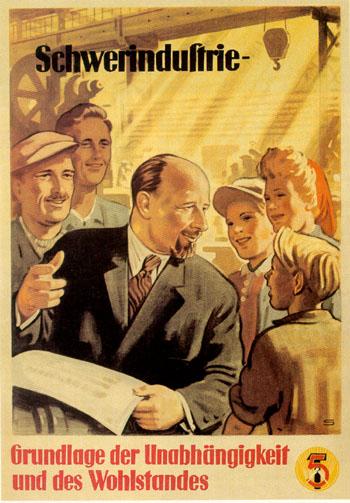
Schließen?! Wo, wenn nicht im Typoforum unter einem thread mit dem Titel Lang-? soll denn über dieses Problem gestritten werden?! Und es wird ja auch niemand gezwungen mitzulesen.
Es wäre vielleicht interessant die verschiedenen Argumente nochmal so zu präzisieren, dass man sich die nächste Debatte zu dem Thema sparen kann mit dem Verweis auf diesen thread. Da wäre den jetzt zu schließen aber wenig hilfreich, dann geht der ganze Spaß beim nächsten mal von vorn los.
Zum Thema:
Ich stimme Thierry zu - Kleinschreibung ist für den Durchschnittsleser weniger irritierend als die verwendung zweier s-Formen.
Ich stimme aber auch Pachulke zu - Die Intension desjenigen der das lange s verwendendet ist vermutlich in den meisten Fällen edler als die desjenigen, der alles klein schreibt. Die Kleinschreibung reduziert die Differenzierungsmöglichkeiten, wärend die verwendung des lange s diese erweitert.
Die Verwendung des langen s führt eine weitere mehr oder weniger komplizierte Regel ein, wärend die konsequente Kleinschreibung eine einfache Regel ignoriert. Das Problem, das es abzuwegen gilt, ist also - Einfachheit gegen Differenzierung. Ich denke, grundsätzlich sind beide erstrebenswert.
vielleicht können wir uns ja auf einen kompromi?s einigen: ? + klein?chreibung ...
Ich meinte mit Beide sind erstrebenswert nicht die Kleinschreibung und die Verwendung des langen s, sondern ganz grundsätzlich Einfachheit und Differenzierung. Da hab ich mich 'n bisschen blöde ausgedrückt.
Auf das lange s aufmerksam zu machen, indem ihr es in allen
Beiträgen verwendet
Es i?t keinesfalls so, da?s ich das lange ? aus?chließlich einsetzen würde, auch ich ?chreibe häufiger normale Texte. Er?t wenn man es mir verbieten will, neige ich dazu es kon?equent zu verwenden … wobei ich es weiterhin recht witzig finde, dass ausgerechnet hier in einem Forum, da?s sich doch mit Typographie be?chäftigt, dem ? ein verhältnismä??ig großer Widerstand entgegen?chlägt. Wobei die Rückmeldungen insgesamt ge?ehen ja durchaus recht breit ge?treut ?ind.
ob die annahme richtig ist, dass das weglassen einer gewohnten differenzierung mehr stört als das hinzunehmen einer ungewohnten.
Das ist natürlich eine grundsätzliche Frage. Rein informationstheoretisch gesehen würde ich diese Aus?age unterschreiben; schließlich kann man alle ? in einem Text mit einem Suchen-und-Ersetzen-Befehl durch das ›normale‹ s ersetzen, wogegen es schwerer wäre ein Programm zu schreiben, dass die korrekte Groß- und Kleinschreibung aus einem Text in konsequenter kleinschreibung rekonstruieren könnte, da man hier mehr Logik (sprich, eine Erkennung der Wortarten) einprogrammieren müsste.
konsequente kleinschreibung verändert das wortbild in der regel an nur einer stelle, nämlich am wortanfang
Aenreerdists snid aebr gadree der estre und der lztete Bcuhasbte für das shcnlele Eafsrsen eeins Woldbirtes boneesdrs whticig, wie diseer ncoh iemmr lbaesre Staz doeniesemtrrn soll!
, und auf spontan vorhersagbare weise. das gilt für das lang-s nicht: dessen verwendung liegt zwar auch eine regel zugrunde, die aber diskutabler und komplexer ist.
Die Regeln sind vielleicht etwas komplexer, aber auch nicht sehr. Die Grundregel lautet einfach Schluss-s am Wortende, sonst langes ?. Alles weitere sind Feinheiten :).
und dann kommt auch noch die vielen fremde buchstabenform ›?‹ ins spiel, die – wie du selbst zugibst – in
… leider viel zu vielen, aber auch nicht in allen Schriftarten …
der antiqua leicht mit einem ›f‹ verwechselt werden kann.
Mir per?önlich i?t das übrigens ?chon lange nicht mehr pa??iert, ich mü??te jetzt er?t länger nachdenken um ein Beip?iel zu kon?truieren, in dem f und ? leicht verwech?elt werden könnten :).
wenn […], und wenn […], ja, dann könnte die verwendung des ›?‹ vielleicht im einen oder anderen fall ohne zu stören für orthogra?sche klarheit sorgen, wo heute der kontext die doppeldeutigkeit auflöst.
hey, du (? für mich ?ieht es irgendwie extrem unhöflich aus, dieses wort klein zu ?chreiben, aber da du es ?o doch lieber ha?t), ver?uch?t meine grund?ätzlichen ?icht (? ganz neues problem: ?ollte man bei kleinge?chriebenen wörtern, die man eigenlich gro?s ?chreiben mü??te, mit ? oder s anfangen? mein gebrochenes herz rät mir hier zum ?) der dinge nachzuvollziehen, auch wenn du die prakti?che um?etzung für nicht pratikabel häl?t!
was das ta?taturlayout angeht, kann ich nur frakturfreaks Empfehlung unter?treichen: es be?teht keine notwendigkeit, noch heute am computer mit einem ta?taturlayout zu ?chreiben, da?s darauf optimiert wurde, da?s ?ich irgendwelche mechnani?che typhebel nicht verhaken!
es geht ja nicht ums mitmachen, sondern erst mal ums verstehen.
So wie Du es ?elb?t be?chrieben ha?t, i?t die kon?equente Klein?chreibung vor allen Dingen ein Produkt der Bequemlichkeit des Schreibers; ich kann das tolerieren, aber ich wü??te nicht, was man da noch weiter ver?tehen mü??te.
ich denke regional gesehen gibts da auch keine verwechslungsgefahr
Ich nehme an, darauf läuft es letztlich heraus: Es gibt keinen überzeugenden Grund, warum ein kleines "f" unbedingt einen Querstrich haben sollte. Wenn mich das irritiert, dann bin ich selber daran schuld, weil ich zu viel erfahren habe über Schriftgeschichte etc.